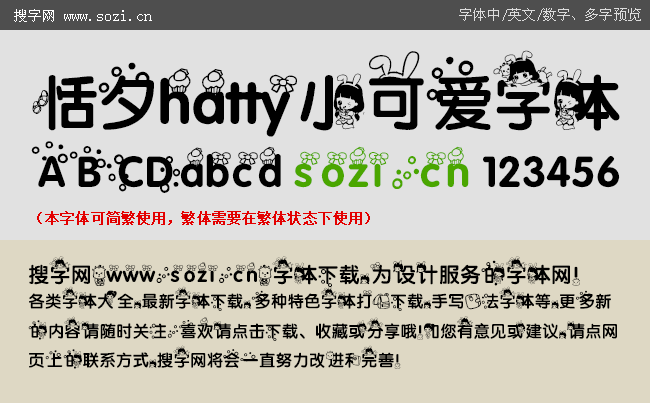
hatty小可愛字體
搜字網(wǎng)給大家提供一款很有趣的手機中文字體下載。修改者給他起名為hatty小可愛字體,這款手機字體是在粗圓體字體筆畫間插入了大量的可愛卡通圖案。在具備粗圓字體醒目清晰端正的風(fēng)格同時,卡通味也特別濃,是一款非?蓯鄣目ㄍㄗ煮w,特別適合喜歡手機字體個性一些的朋友在手機上安裝使用。